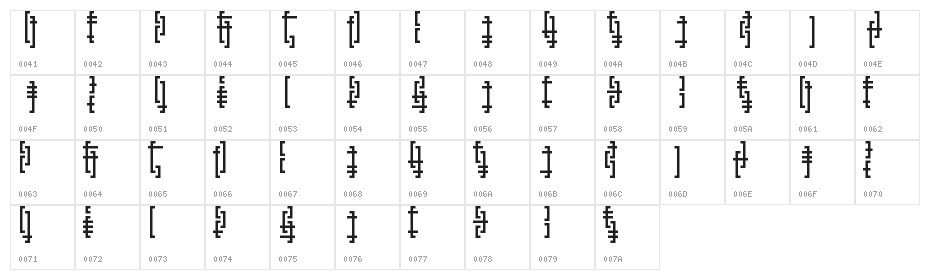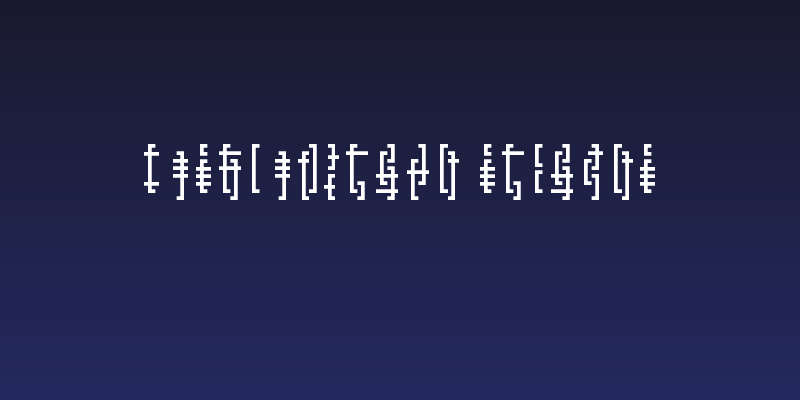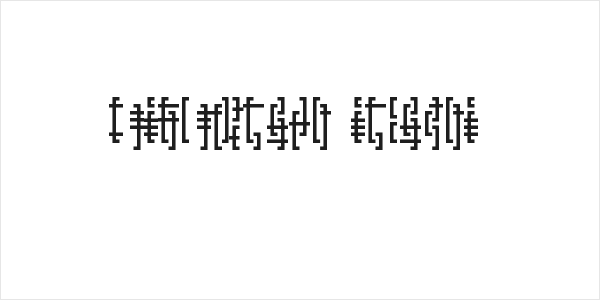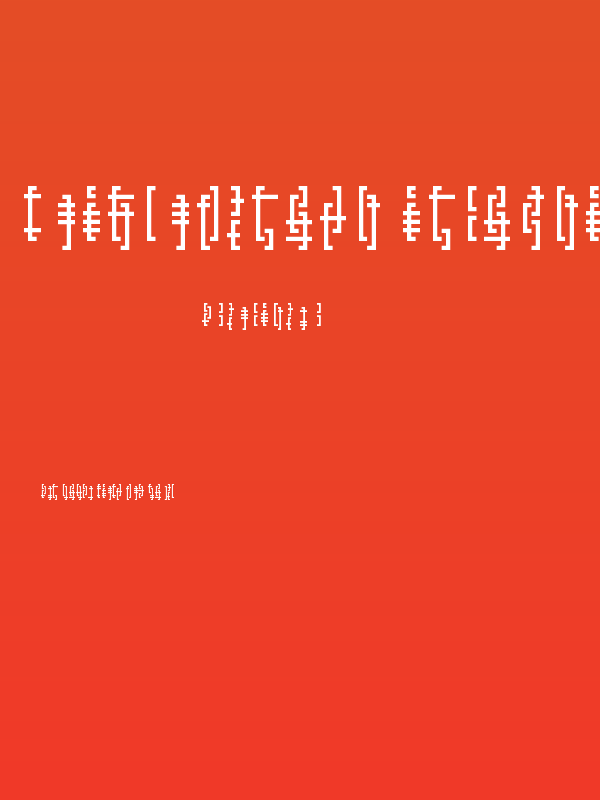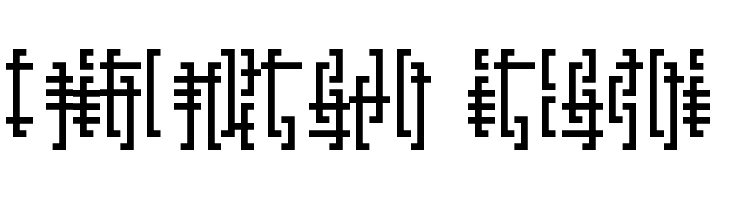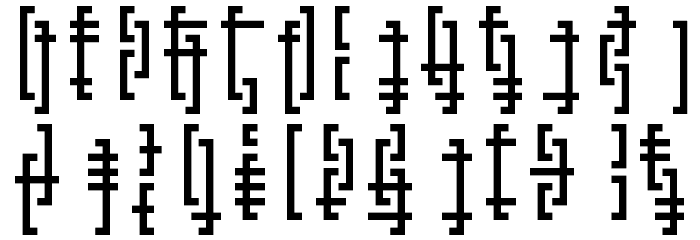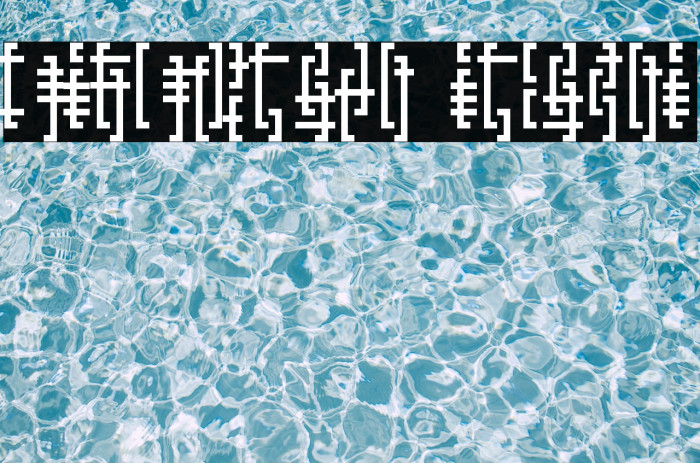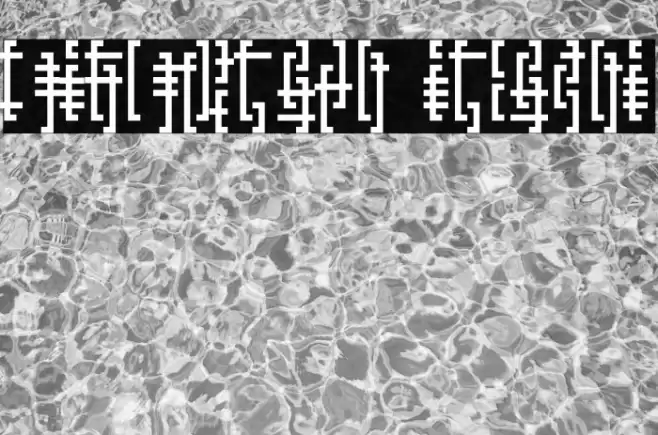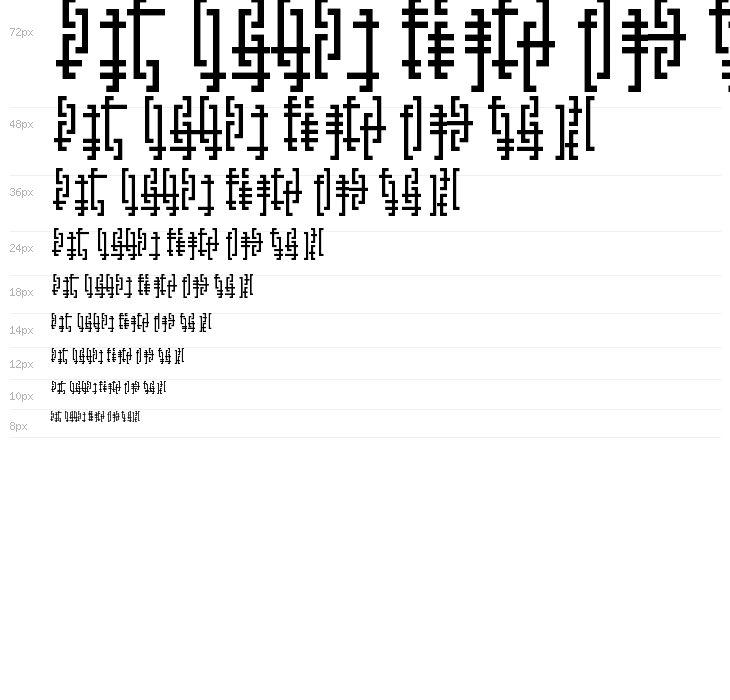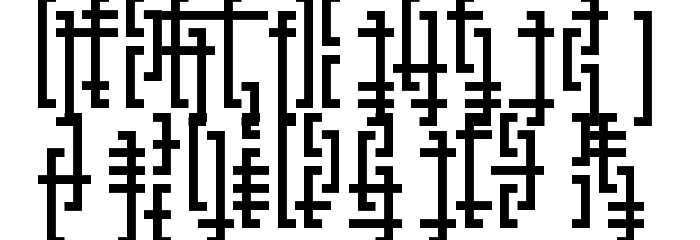
wordsofpeuna Regular Font
| Stile generale | Futuristic, Abstract |
| Caso d'uso | Logos, Posters, Artistic Projects |
| Progetti proposti | Ideal for artistic designs, digital art, futuristic themes, or branding that requires a unique and striking typeface. |